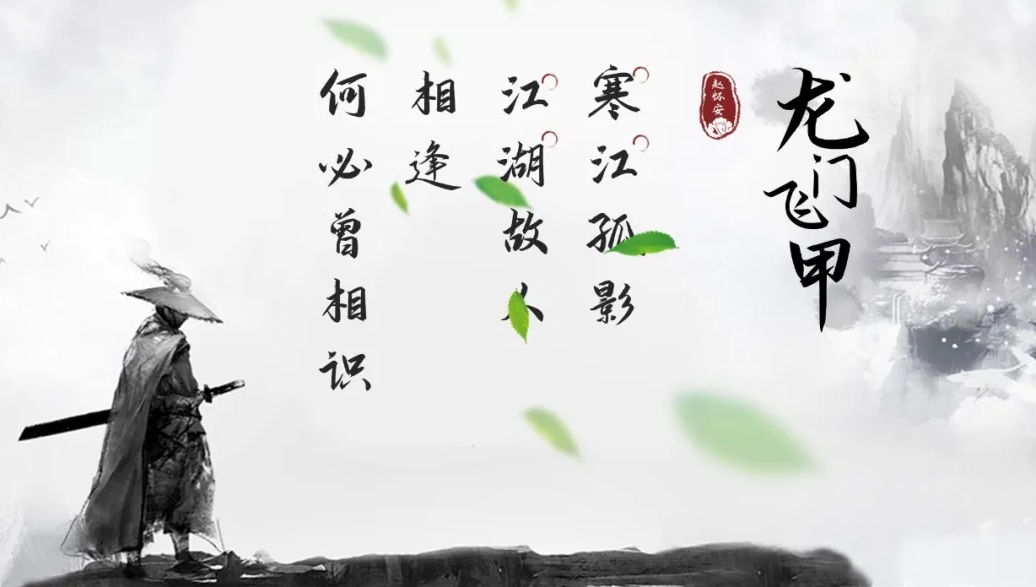
演示悠然小楷
演示悠然小楷,一款由秋叶联合keynote研究所推出的书法字体,其字稿的创作出自孟祥媛,一位尚在大学攻读的书法专业学子。
初次接触“演示悠然小楷”,可能会让你觉得并无特别惊艳之处,但仔细品味,你能察觉到其中蕴含的质朴与率真的气息。这犹如作者本人,尚处于象牙塔中的书卷气,未经世俗雕琢的朴拙。下面,让我们一同探寻悠然小楷中的这份“拙气”。
演示悠然小楷的笔画清晰明了,结构一目了然,没有过度的连笔与飞白,使得阅读时更加轻松识别。小楷的字形虽小,却有着适度的字间距,即便用于长篇文字,阅读上也不会感到太大的视觉压力。
在笔画力度上,演示悠然小楷分布均衡,起收有序,没有过于强烈的对比,显现出沉稳而不浮夸的特点。同时,在小楷的基础上融入了一些行楷的元素,为字体增添了几分灵动,却又不过分张扬,形成了独特的停而不断、笔断意连的风格。另外,部分笔画细节可能显得并不完美,有些粗糙,这份未经雕琢的朴拙,又何尝不是一种难能可贵的特质。
在欣赏过众多大开大合的书法字体后,再次遇见演示悠然小楷,可能无法立即感受到其惊艳之处。然而,艳丽与喧嚣并不代表力量,沉稳而有力才是更为宝贵的品质。
演示悠然小楷效果预览